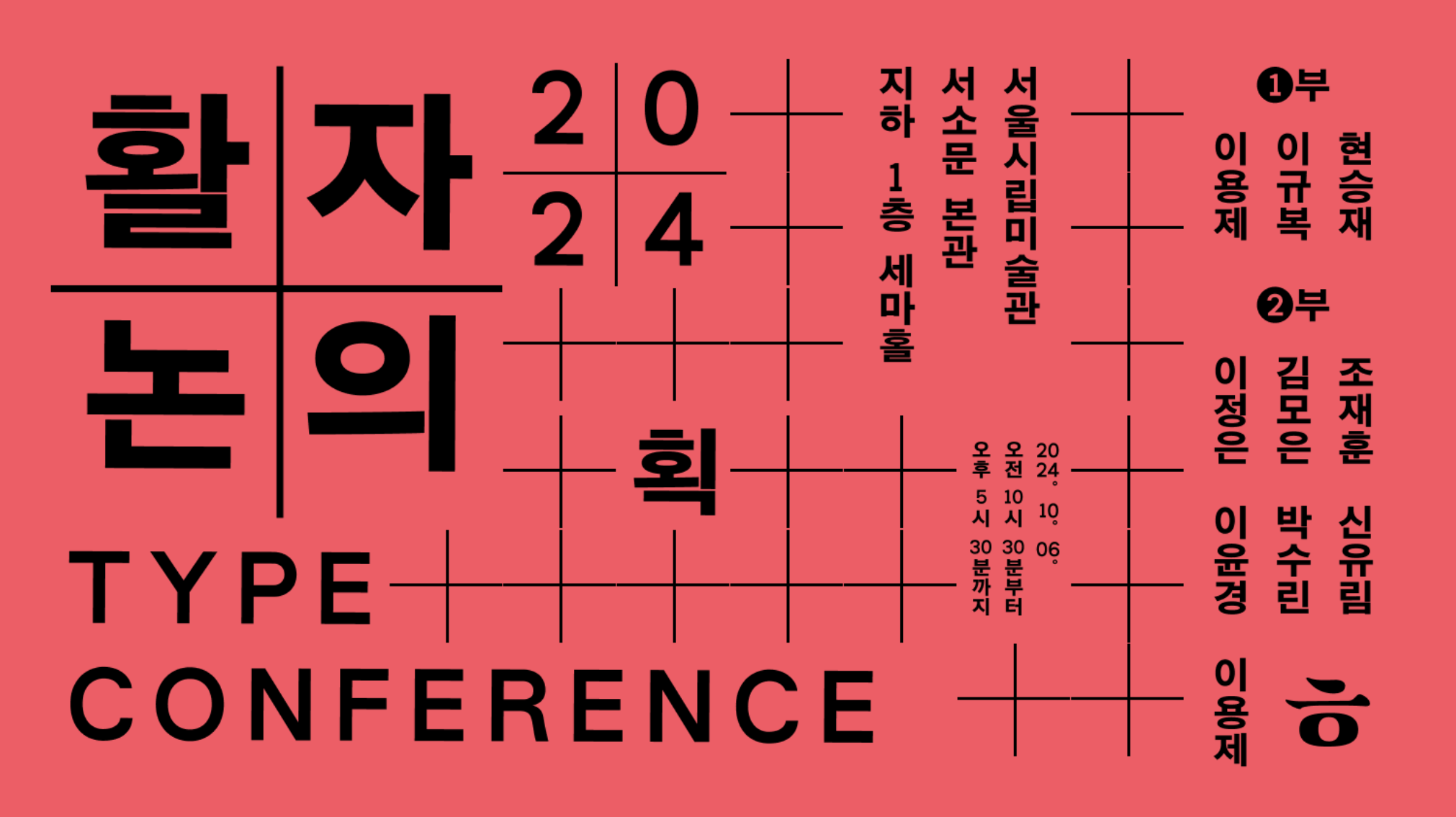
한글의 글자 표현을 확장하기 위해 다시 획을 주목해야 한다는 믿음으로,
[활자논의] 2024는 레터링과 활자의 표현을 살펴보고, 한글 명조체 표현의 출발점인 궁서체의 획에 대해서 논의한다.
그리고, 오랜 역사를 가진 한글 명조체와 고딕체의 표현과 최정호가 정립한 현대 한글 활자의 표현을 논의한다.